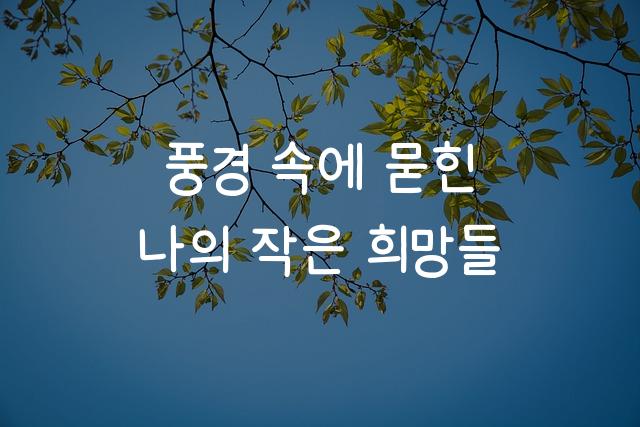
거친둘기마요는 삐뚤빼뚤하고 색연필로 그려진 듯한 독특한 감성을 지닌 폰트입니다. 창의적이고 편안한 느낌을 주어 디자인에 유니크한 터치를 추가합니다.
거친둘기마요은(는)
색연필 계열의 생김새를 가지고 있으며
포스터, 광고 캠페인, 브랜딩 등에서 자주 활용되며, 효과적인 메시지 전달에 적합합니다.
이 폰트는 광고/마케팅, 크리에이티브, 문화/예술 분야에 잘 어울리며,
세련된, 창의적인, 강렬한 느낌을 담고 있는 것이 특징입니다.